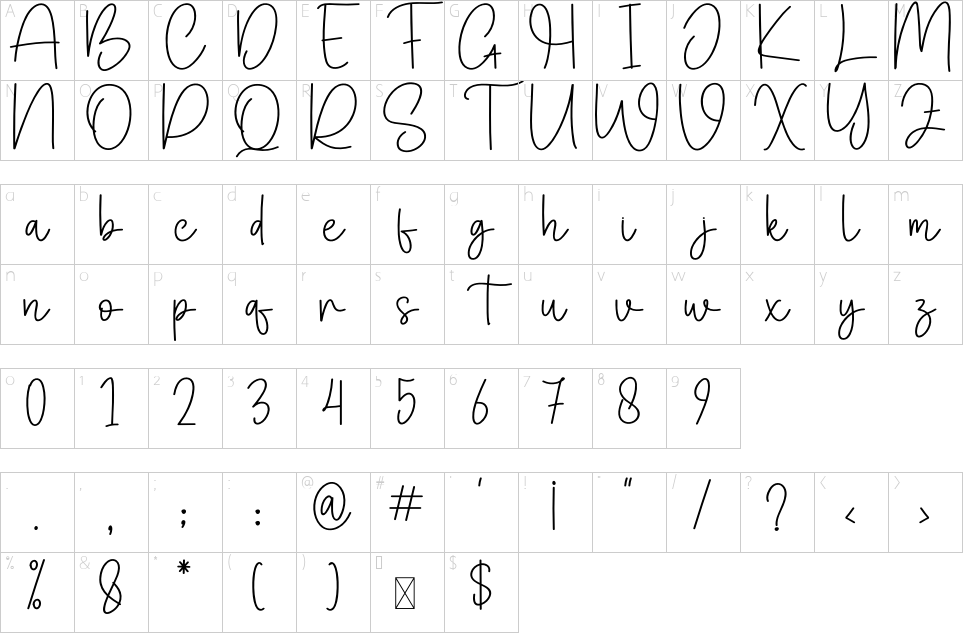
Descubra a elegância e a simplicidade da Mama Font, uma elegante fonte criada pelo designer scratchones. Baixe a Mama Font para Windows e Mac, uma opção grátis e versátil para personalizar seu layout digital. Essa fonte, desenhada pensando no conforto visual e na legibilidade, já foi baixada 412 vezes, demonstrando sua popularidade entre designers e criadores de conteúdo. Composta de linhas finas e elegantes, a Mama Font é perfeita para títulos, pequenos textos e até mesmo design gráfico, proporcionando um toque especial e sofisticado a seus trabalhos. Experimente agora a Mama Font e transforme sua interface digital em algo único e atraente.